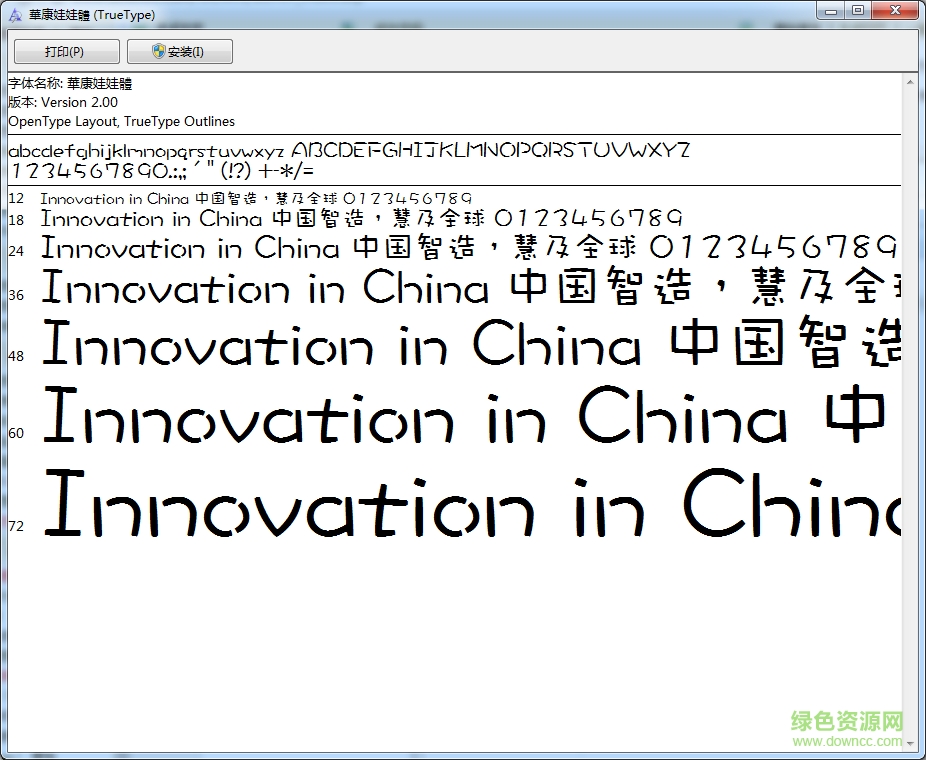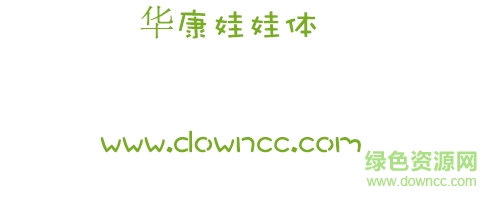
華康娃娃體是一款非常美觀大方的電腦字體軟件,以可愛(ài)風(fēng)為主要特色,常用于美工設(shè)計(jì)和圖文印刷等多種領(lǐng)域,一鍵安裝安裝便可免費(fèi)使用??靵?lái)綠色資源網(wǎng)下載體驗(yàn)吧!
可愛(ài)風(fēng)格設(shè)計(jì)的手寫(xiě)字體,它能夠?yàn)橛脩?hù)提供中英文雙語(yǔ)字體,娃娃體雖然不夠端正,但是別具童真氣息,非常受用戶(hù)的喜歡,本款中文為繁體字。
華康娃娃體是一款非常受歡迎的字體,在外型及風(fēng)格上,華康娃娃體的筆劃類(lèi)似于兒童書(shū)寫(xiě),非常稚嫩可愛(ài),常常被用于卡通設(shè)計(jì),不過(guò)這當(dāng)然也能用來(lái)做平時(shí)使用的字體。